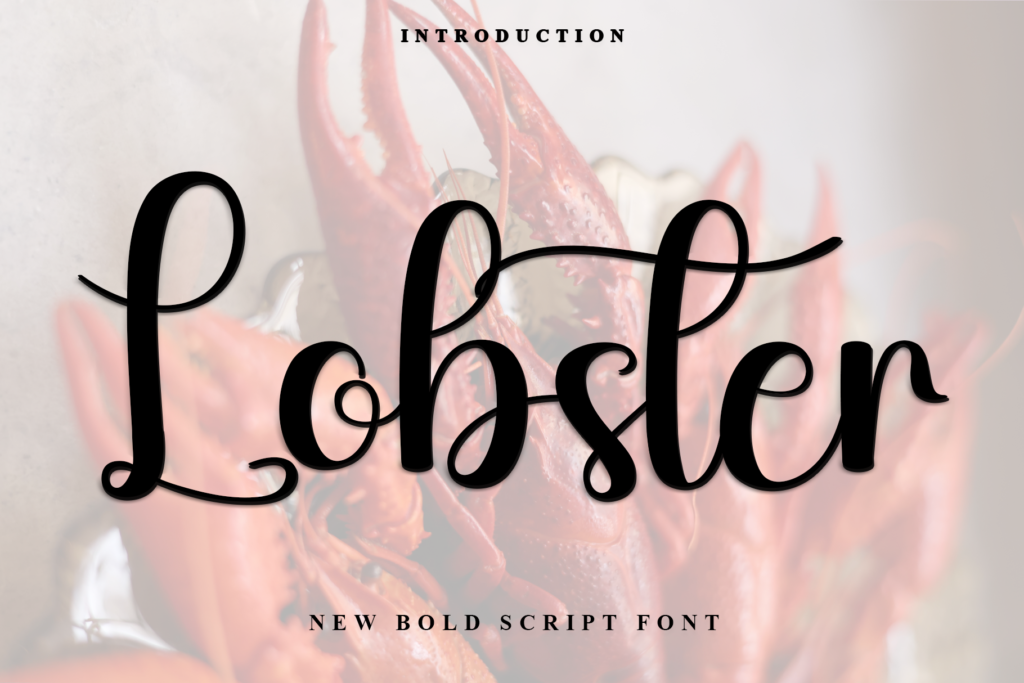
Font gratis untuk desain kaos yang tepat adalah kunci agar desain terlihat keren tidak hanya di layar tetapi juga setelah dicetak di atas kain. Memilih font ternyata tidak sesederhana mencari yang terlihat bagus: ukuran, ketebalan huruf, jarak antarhuruf, warna kaos, hingga metode printing semuanya berpengaruh pada hasil akhir yang sesungguhnya.
Kabar baiknya, banyak sekali font gratis untuk desain kaos yang bisa langsung digunakan untuk mengeksplorasi berbagai konsep mulai dari font bold untuk desain sporty, sans-serif bersih untuk tampilan minimalis, hingga font retro dan playful untuk kaos dengan karakter yang lebih kuat dan berkesan. Menurut Adobe, pemilihan typography yang tepat secara langsung menentukan persepsi nilai sebuah produk sebelum orang sempat membaca pesannya.
Berikut 12 font gratis untuk desain kaos terbaik beserta tips memilih font yang tepat agar desainmu siap diproduksi.
Mengapa Pemilihan Font Gratis untuk Desain Kaos Sangat Penting?
Dalam desain kaos, font bukan hanya berfungsi menyampaikan tulisan tetapi jenis huruf yang dipilih juga secara langsung membangun karakter visual keseluruhan desain.
- Font tebal dan condensed → kesan sporty, kuat, dan dinamis
- Font geometris bersih → tampilan modern dan minimalis
- Font script → kesan santai, personal, atau vintage
- Font slab serif → nuansa retro dan berkarakter kuat
Selain karakter visual, keterbacaan adalah faktor yang tidak bisa dikompromikan. Desain kaos biasanya dilihat dari jarak tertentu sehingga tulisan harus tetap mudah dikenali. Font dengan detail terlalu tipis atau terlalu rumit berpotensi membuat tulisan tidak terbaca saat dicetak dalam ukuran kecil.
12 Font Gratis untuk Desain Kaos Terbaik
1. Bebas Neue — Sporty dan Tegas
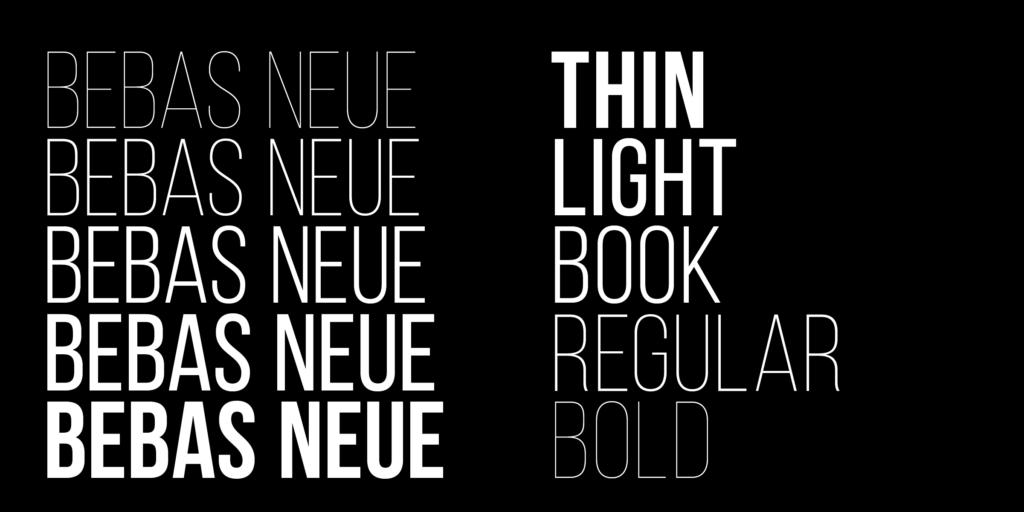
Bebas Neue adalah font gratis untuk desain kaos yang paling banyak digunakan seperti bentuk hurufnya tinggi, ramping, dan condensed sehingga tulisan terlihat menonjol tanpa membutuhkan area desain yang terlalu lebar.
Font ini sangat efektif untuk slogan, nama brand, dan desain bertema olahraga. Bentuknya yang simpel membuat keterbacaan tetap terjaga bahkan dalam ukuran besar.
Cocok untuk: Desain sporty, streetwear, dan typography kaos.
2. Anton — Bold dan Dominan
Jika ingin tampilan yang lebih tebal dan kuat, Anton adalah pilihan font gratis untuk desain kaos yang sangat tepat. Bentuk hurufnya solid dengan karakter yang cukup dominan dan cocok sebagai fokus utama desain.
Anton juga bisa dikombinasikan dengan font yang lebih simpel untuk menciptakan hierarki visual yang kuat.
Cocok untuk: Slogan, typography kaos, desain statement, dan streetwear.
3. Montserrat — Modern dan Fleksibel
Montserrat adalah sans-serif dengan bentuk geometris yang bersih dan sangat modern. Fleksibilitasnya membuatnya bisa digunakan untuk hampir semua konsep desain kaos.
Gunakan bobot Bold atau ExtraBold jika tulisan ingin menjadi elemen utama. Bobot yang lebih ringan cocok untuk teks pendukung.
Cocok untuk: Desain minimalis, modern, brand, dan custom kaos.
4. Poppins — Bersih dan Friendly
Poppins memiliki bentuk geometris dengan karakter yang lebih rounded dibanding kebanyakan sans-serif lainnya sehingga hasilnya terlihat modern dan bersih, tetapi tetap terasa hangat dan friendly.
Cocok untuk: Desain modern, casual, lifestyle, dan typography kaos yang tidak terlalu formal.
5. Oswald — Condensed untuk Teks Panjang
Oswald memiliki karakter condensed yang sangat praktis agar tulisan panjang bisa tetap terlihat ringkas dan elegan. Font ini juga memiliki kesan tegas yang cocok untuk desain bertemakan olahraga atau aktivitas fisik.
Cocok untuk: Sportswear, jersey, streetwear, dan desain kaos dengan banyak teks.
6. Archivo Black — Sangat Tebal dan Berkarakter
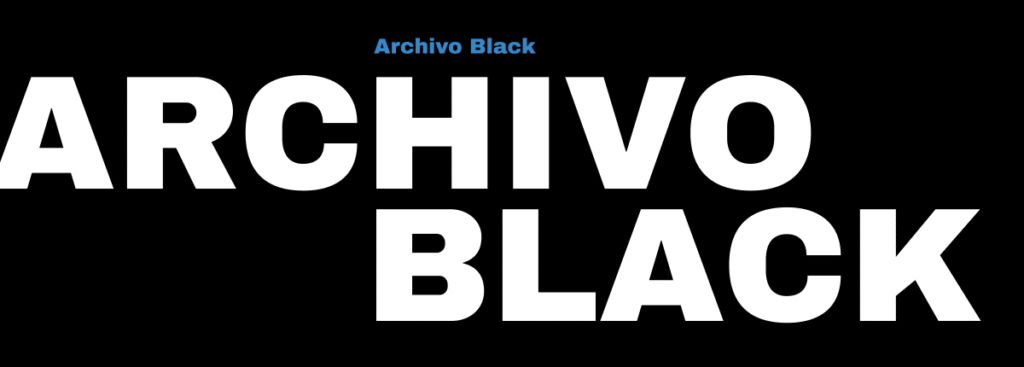
Archivo Black menawarkan bentuk huruf yang sangat tebal dengan area karakter yang solid. Untuk desain dengan satu atau beberapa kata sebagai fokus utama, font ini memberikan dampak visual yang sangat kuat.
Catatan: Pastikan warna tulisan memiliki kontras yang cukup dengan warna kaos karena karakternya yang sangat bold.
Cocok untuk: Desain statement, slogan pendek, dan typography bold.
7. Alfa Slab One — Retro dan Sporty
Ingin membawa nuansa retro ke desain kaos? Alfa Slab One adalah font gratis untuk desain kaos dengan karakter slab serif yang tebal dan sangat khas untuk memberikan kesan vintage sekaligus sporty.
Cocok untuk: Desain retro, vintage, sportswear, dan merchandise komunitas bertema old-school.
8. Righteous — Geometris dengan Sentuhan Retro
Righteous memiliki karakter geometris dengan sentuhan visual yang terinspirasi dari era 1970-an hingga 1980-an. Pilihan menarik ketika ingin membuat desain kaos yang terasa unik sekaligus tetap mudah dibaca.
Cocok untuk: Desain retro, lifestyle, dan typography kreatif.
9. Bangers — Playful dan Ekspresif
Yang paling penting: pilih font berdasarkan konsep desain, perhatikan ketebalan dan keterbacaan, batasi jumlah font, pastikan kontras warna, dan selalu cek lisensi untuk kebutuhan komersial. Setelah desain siap, pastikan proses printing juga mendukung, karena font yang keren hanya akan tampil maksimal jika dicetak dengan teknologi yang tepat.